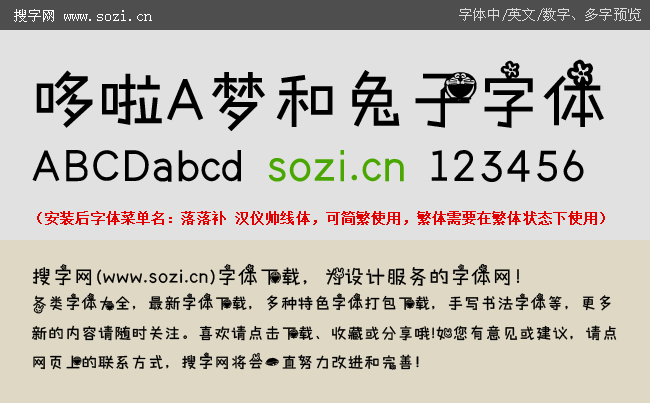
哆啦A夢(mèng)和兔子字體
搜字網(wǎng)給大家提供一款哆啦A夢(mèng)和兔子字體手機(jī)中文字體下載。這款手機(jī)字體是以漢儀帥線體為原形,字體中被嵌入了哆拉A夢(mèng)等卡通圖案,這款字體卡通味特別濃,特別適合喜歡手機(jī)字體個(gè)性一些的朋友在手機(jī)上安裝使用。